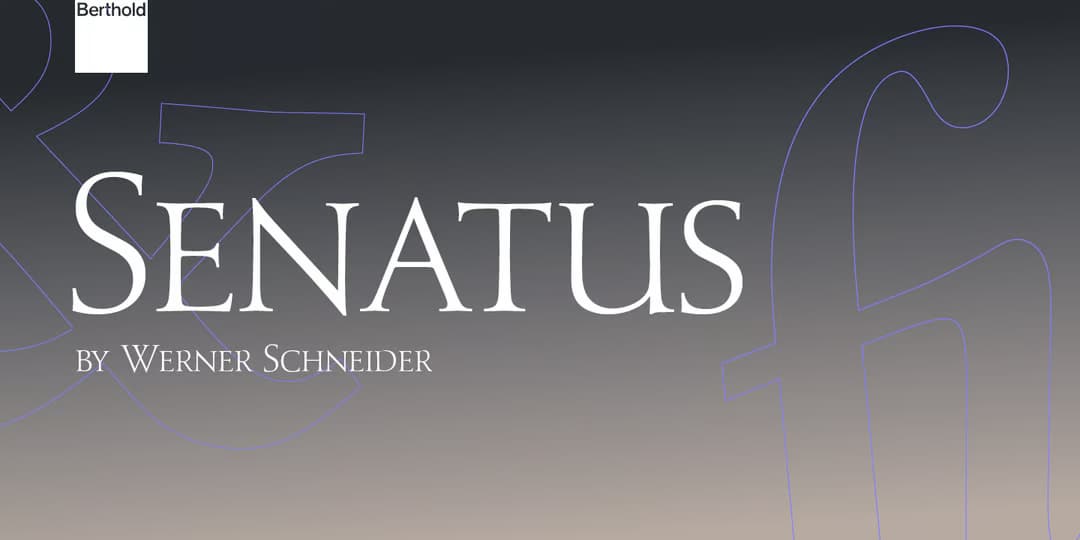
Senatus
久々に紹介する碑文系ローマンキャピタルディスプレイ。まあ Trajan でいいじゃんとなるぐらいにはこれといった特徴はないが(笑)、これは数ある同種の書体の中でもかなり出来の良い方だと思う。非常にシンプルな書体ではあるが、それだけにちょっとした線の狂いでバランスが崩れるので、かなり細かく調整したんじゃないだろうか。大変威風堂々としていて美しい。よ~く見ないと違いが分からないが、オールドスタイル数字があるのがめずらしい。名前はラテン語で「元老院」の意味で、古代ローマ帝国の御触書の冒頭は「Senātus Populusque Rōmānus(ローマの元老院と人民へ告ぐ)」が決まり文句だった。略して「SPQR」と書くこともある。